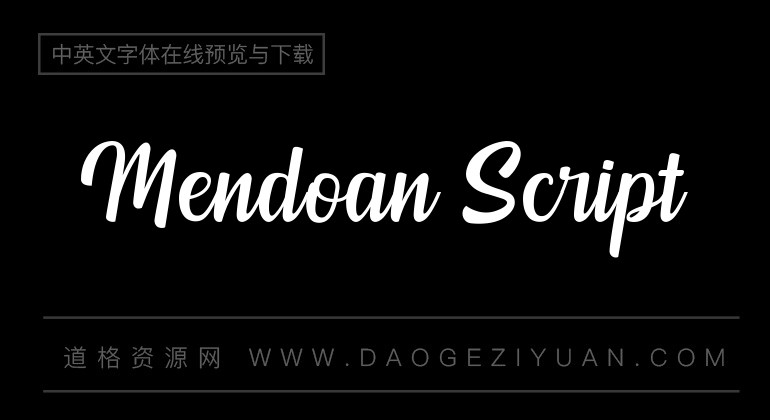
Mendoan Script 是一款手写风格的英文字体,它拥有比较柔和的曲线,以及比较大的英文字母,使得整个字体看起来更加温柔,更加优雅。它的设计灵感来自一个古老的秘鲁文化,可以提供给您更多的灵感,使您的文字变得更加有趣。Mendoan Script 字体可以用于各种类型的印刷品,如海报、书籍封面、婚礼邀请函等,也可以用于网页设计,使您的网站更加温馨可爱。内容介绍
Mendoan Script是一款非常不错的手写艺术字体,具有很好的视觉感,适合于文化类的宣传设计、商业类品牌的广告和产品包装设计以及个性化文字排版等较多场景。